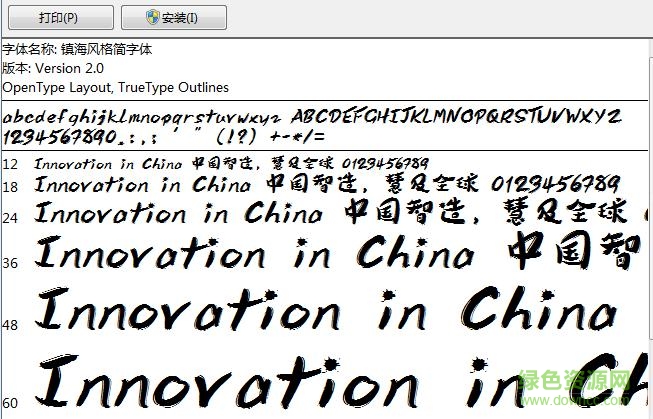
鎮(zhèn)海風(fēng)格簡(jiǎn)字體常規(guī)體
鎮(zhèn)海風(fēng)格簡(jiǎn)字體是一款極具風(fēng)格的中文字體,字形看上去有點(diǎn)q萌,整體看上去非常的靈動(dòng)可愛,適合用來(lái)進(jìn)行各種藝術(shù)的創(chuàng)作,感興趣歡迎下載!
鎮(zhèn)海風(fēng)格簡(jiǎn)字體簡(jiǎn)介
鎮(zhèn)海風(fēng)格簡(jiǎn)字體是一款非常有特點(diǎn)的毛筆書法字體,飄逸灑脫的造型給人隱士名流之感,無(wú)論是設(shè)計(jì)印刷、打印排版還是廣告創(chuàng)意,使用都有益處!
鎮(zhèn)海風(fēng)格簡(jiǎn)字體